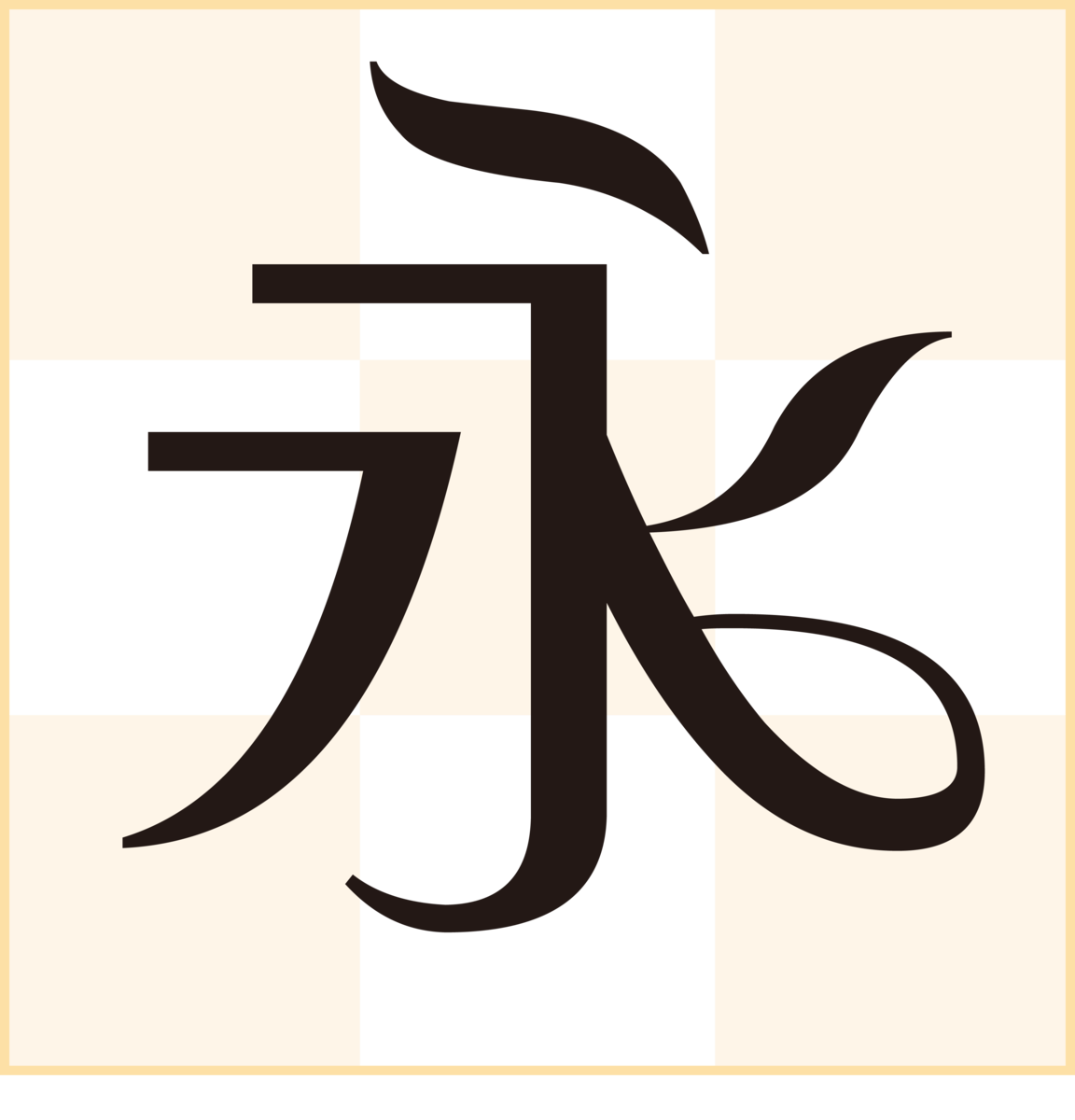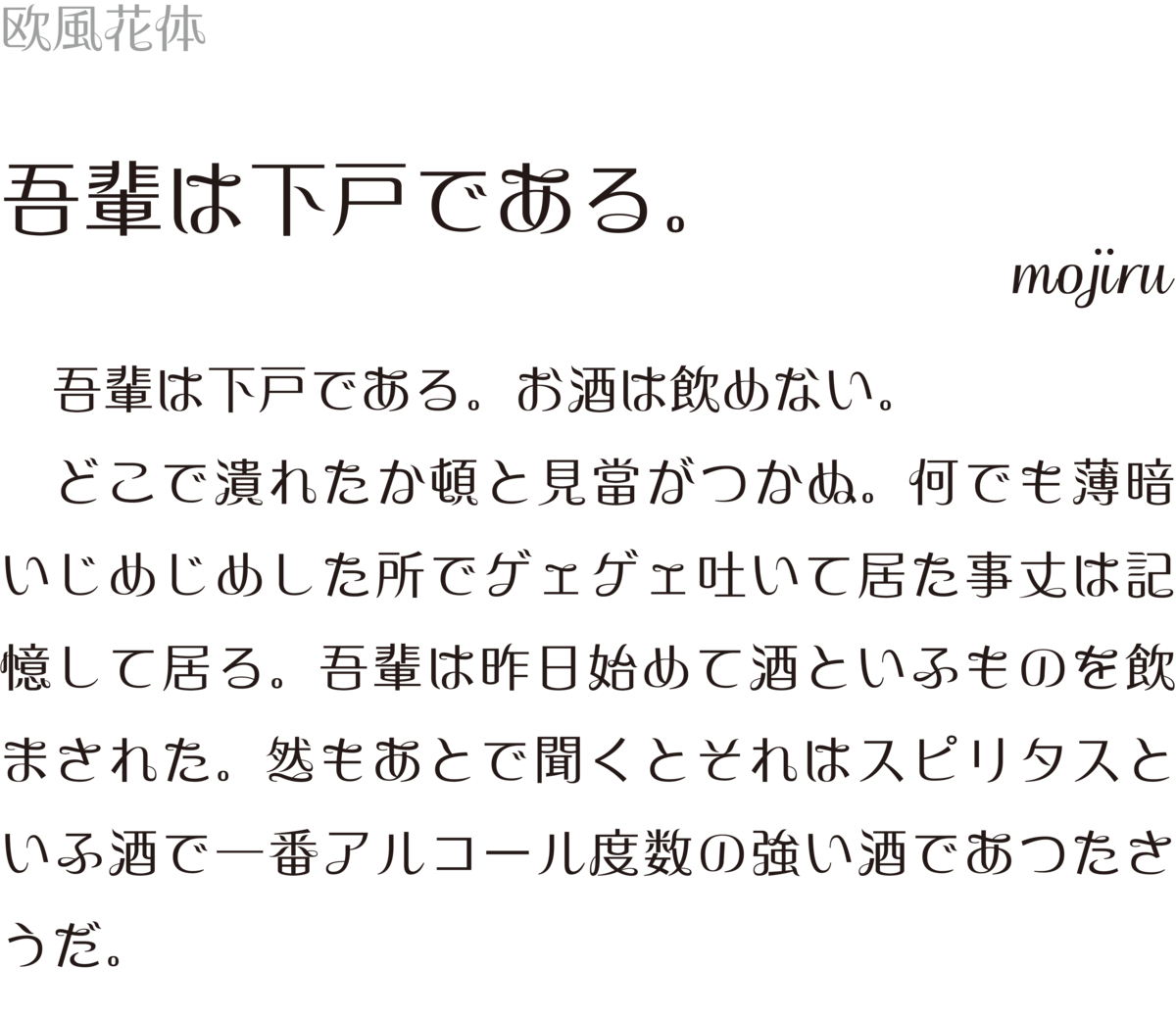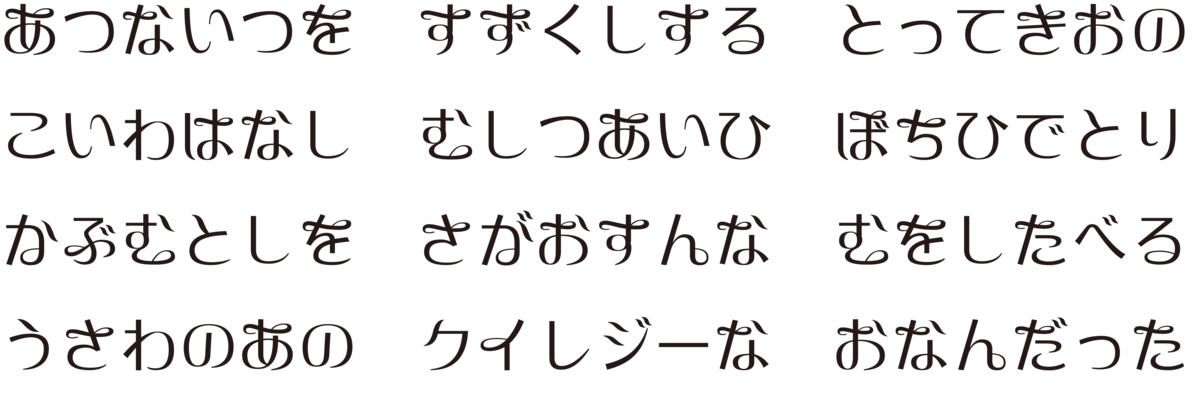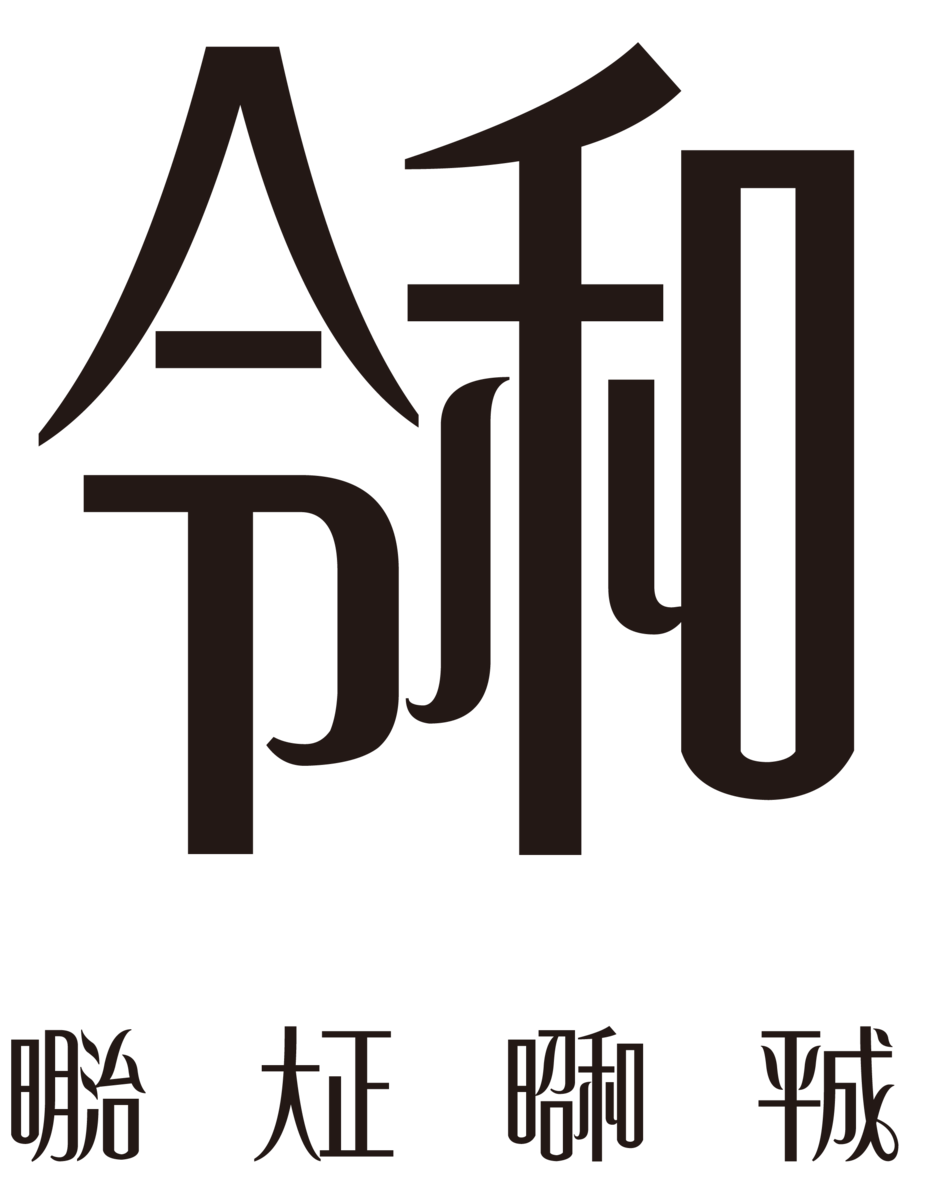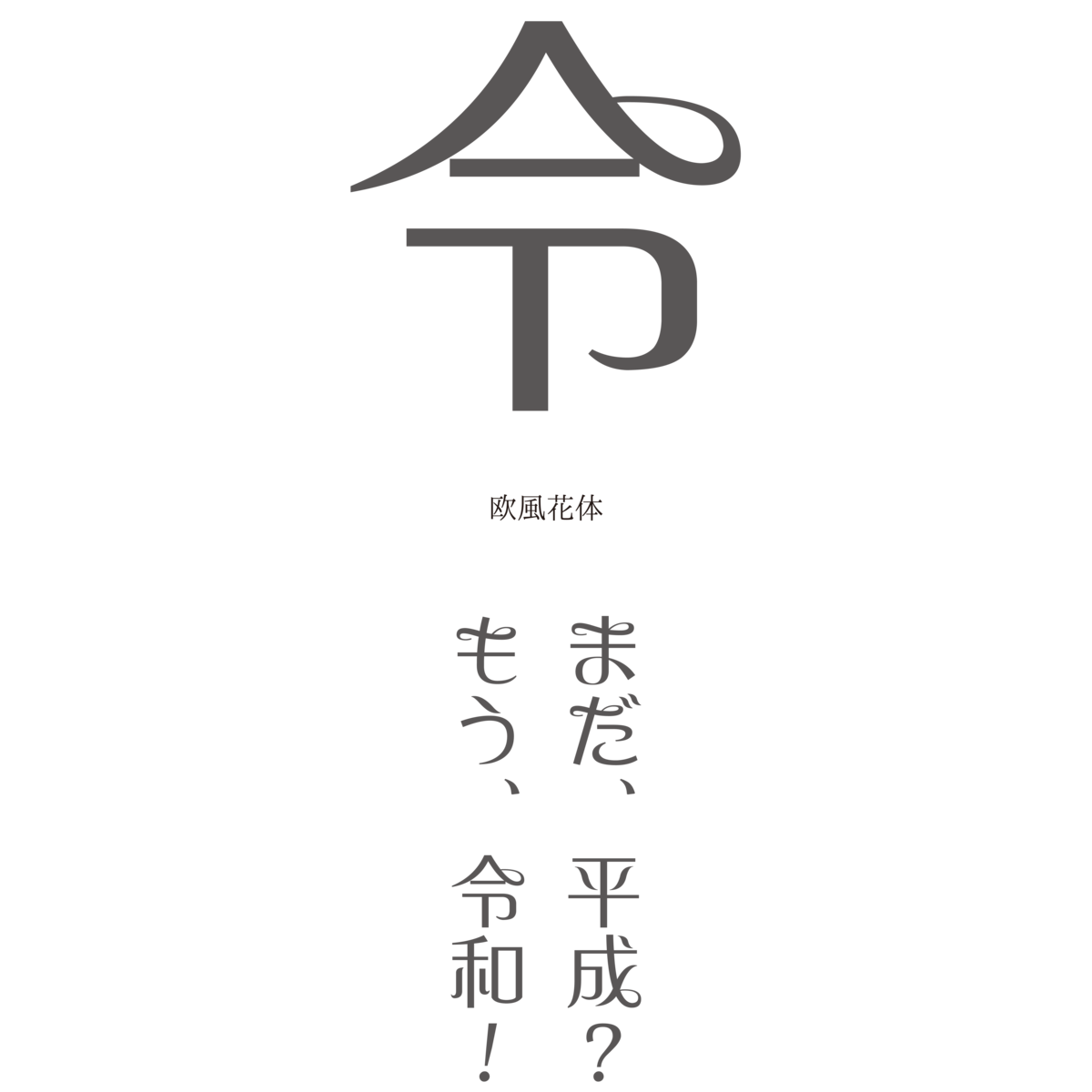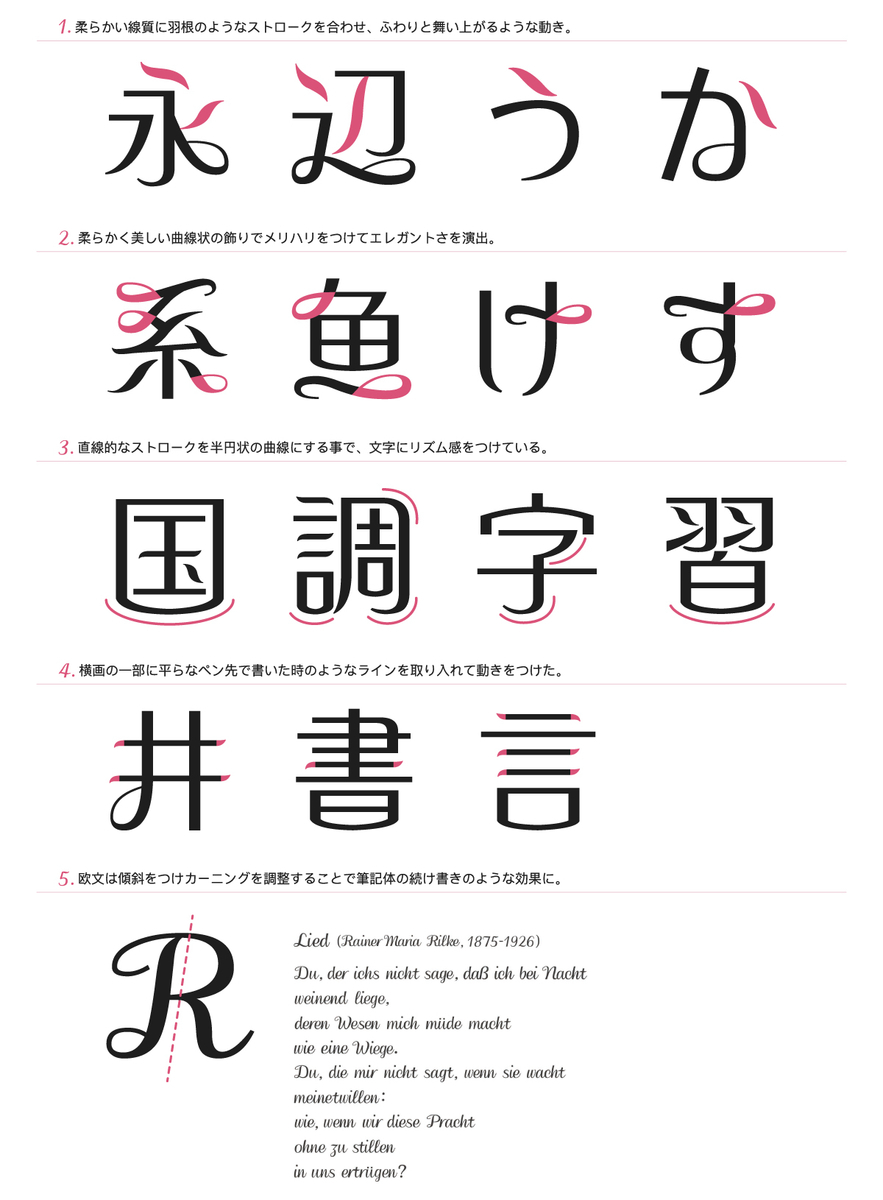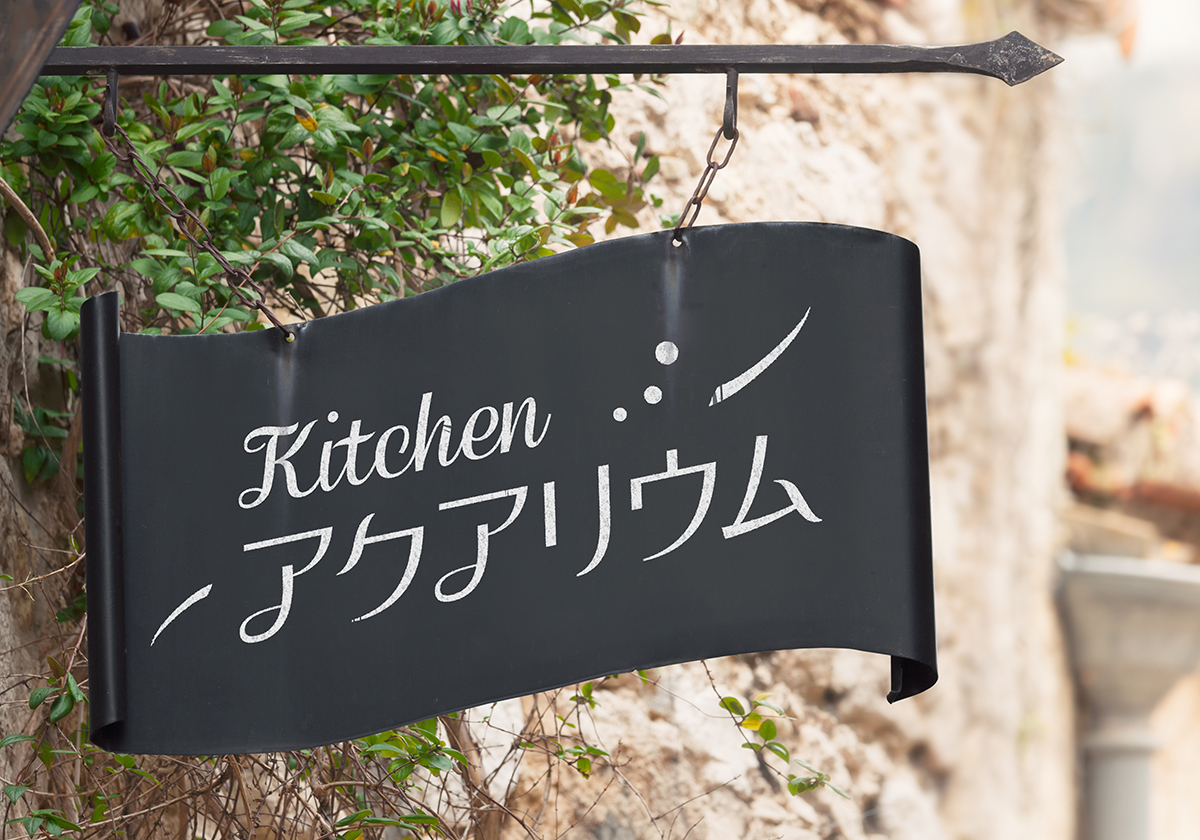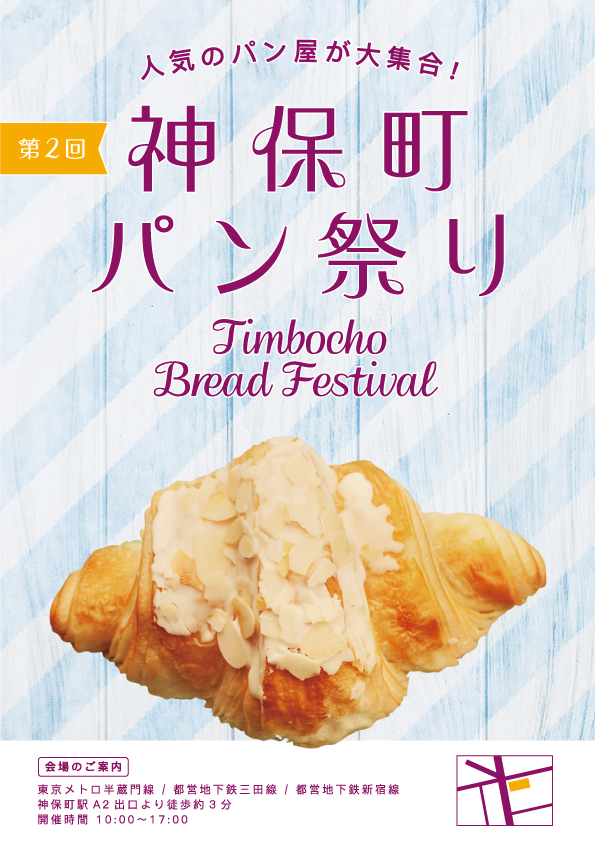
欧風花体
「欧風花体」は、リズミカルな筆遣いの文字にループが特長的な書体。欧文の手書き文字を参考にしており、漢字や平仮名のデザインにもカリグラフィー特有の滑らかで抑揚のあるループを取り入れられている。カーニングを調整することで、筆記体の続け書きのような効果を生み出している。
欧風花体の書体見本
欧風花体の「令和」書体見本
欧風花体の特徴
欧風花体の活用例
TVアニメ「かげきしょうじょ」の予告に、ダイナフォント年間ライセンス「DynaSmart V」および収録書体「欧風花体」が採用
TVアニメ「かげきしょうじょ!!」の予告の文字に、ダイナフォント年間ライセンス「DynaSmart V」および収録書体「欧風花体」が採用されている。
「欧風花体」は、2019年2月に開催されたイベント「page2019」での情報が初解禁されたリズミカルな筆遣いの文字にループが彩られた、見る者の心を揺さぶる洗練された書体。